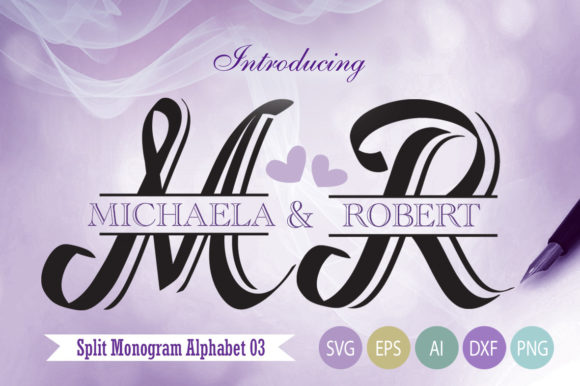
Calligraphic Split Monogram Svg Letters
Si vous recherchez des ressources de haute qualité comme Calligraphic Split Monogram Svg Letters, ce pack premium est un choix fantastique pour vos projets créatifs.
Que vous créiez des produits POD (impression à la demande), des invitations de mariage ou des visuels pour les réseaux sociaux, Calligraphic Split Monogram Svg Letters est un choix idéal.